Есть множество различных типов шрифтов, которые вы можете использовать для того, чтобы придать вашему дизайну более профессиональный и деловой вид.
Но лучше всего с этой задачей справятся геометрические шрифты — их идеально ровный дизайн букв сделает ваш дизайн аскетичным и в то же время стильным.
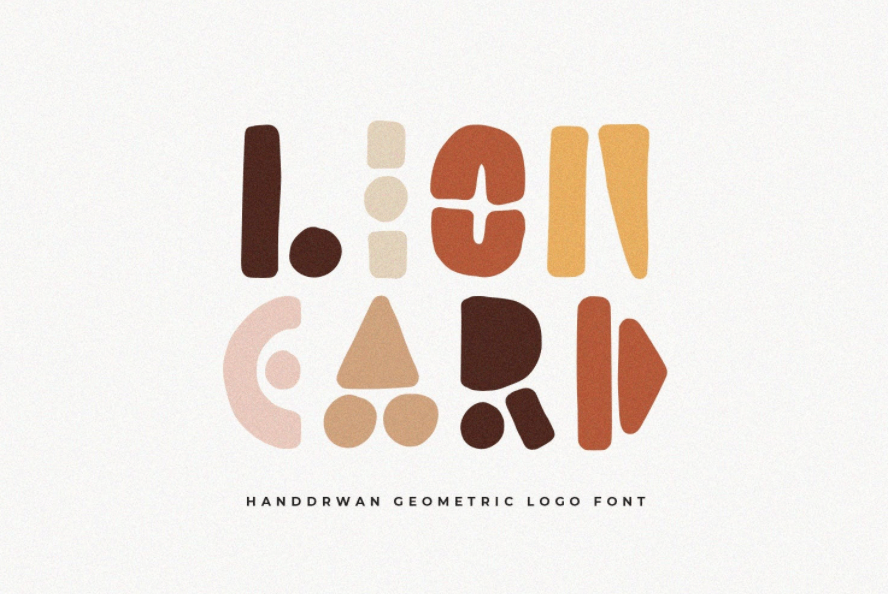
Lion Card — это геометрический шрифт ручной работы, который не оставит равнодушным ни одного пользователя. Он имеет уникальный дизайн, который идеально подходит для творческих проектов по брендингу. Этот красочный и забавный шрифт состоит из прописных букв, цифр и знаков препинания.
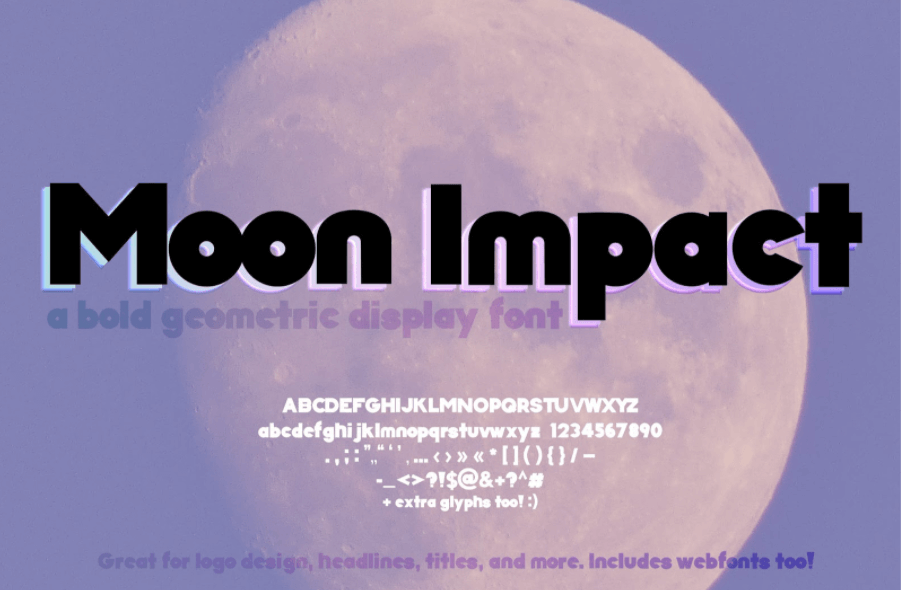
Moon Impact — это смелый геометрический шрифт, который подходит для множества проектов, связанных с созданием логотипов, заголовков и постеров. Moon Impact — это гладкий шрифт с округлыми буквами и тенью.
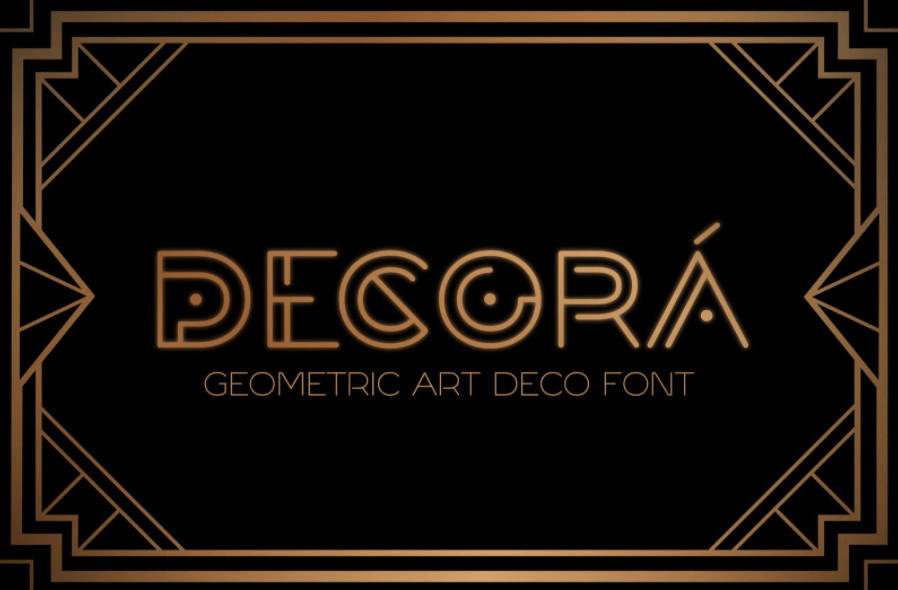
Вдохновленные движением 20-х годов ар-деко, создатели Decora разработали роскошный, винтажный шрифт, который при этом выглядит очень актуально и современно. Вы можете использовать его для заголовков-веб сайтов, а также для любых других элементов цифрового дизайна.
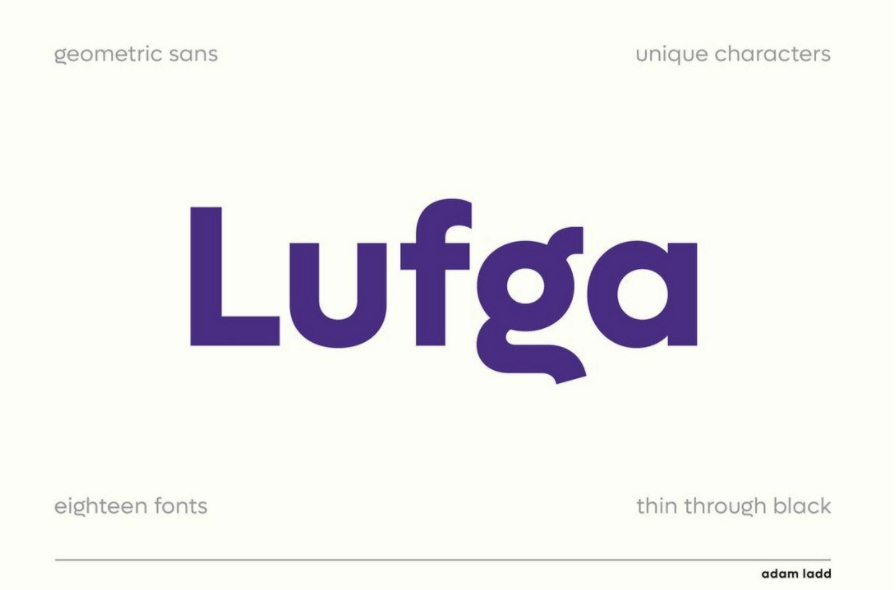
Lufga — это один из самых уникальных шрифтов в этой подборке. Каждый изгиб букв этого шрифта выглядит совершенным и идеальным. Lufga — это целое семейство шрифтов с 18-ю различными вариантами начертания. Шрифт идеально подходит для заголовков веб-сайтов, логотипов, визитных карточек и заголовков плакатов.
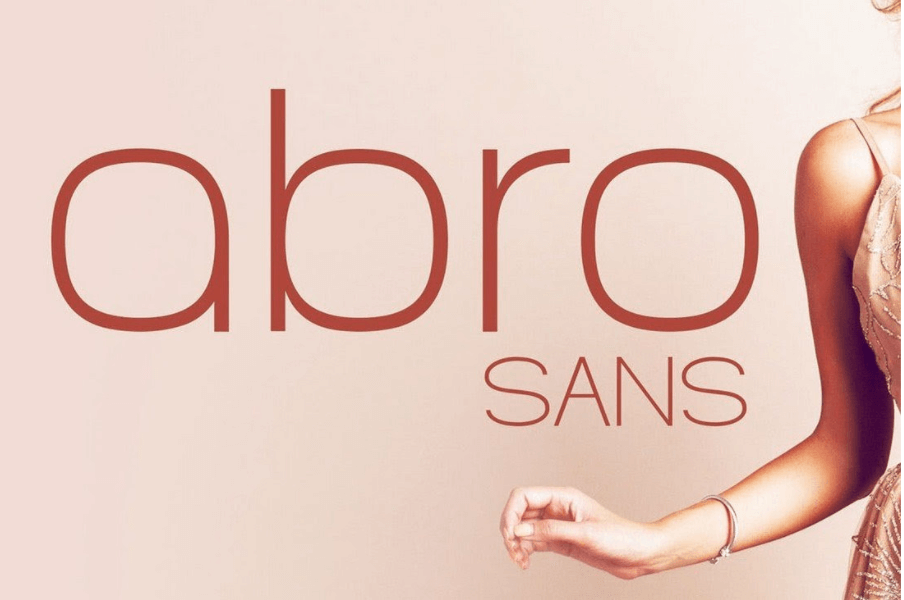
Abro — это геометрический шрифт с элегантным дизайном. Он поставляется с 3-мя различными начертаниями шрифта, а также содержит более 300 глифов. Шрифт Abro — универсальный и идеально подходит для веб-сайтов с различными тематиками.
Четкий дизайн без засечек — это одна из особенностей, которая выделяет дизайн этого шрифта среди нашей подборки. Ageo — это геометрический шрифт, который можно использовать в различных дизайнерских проектах.
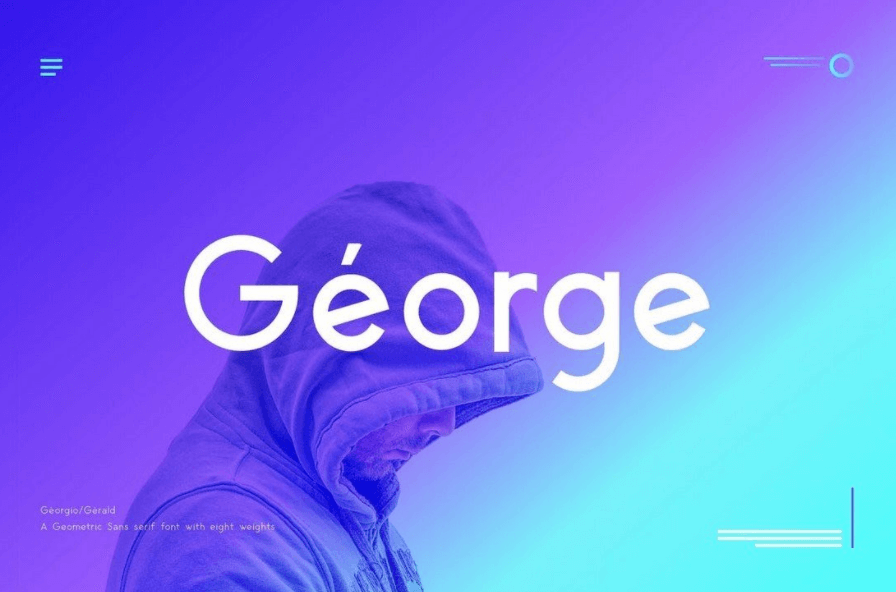
Создаете ли вы заголовок веб-сайта, публикацию в социальных сетях или плакат, этот геометрический шрифт добавит вашему проекту уникальности и оригинальности.
У George Sans аккуратный и четкий дизайн букв, поэтому он выглядит очень строго, но в то же время стильно. Шрифт имеет 8 вариантов различной толщины и многоязычную поддержку.